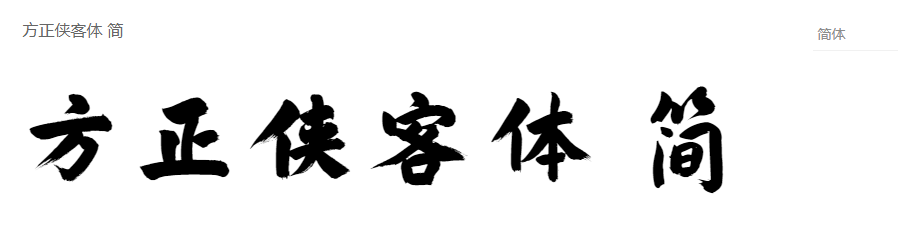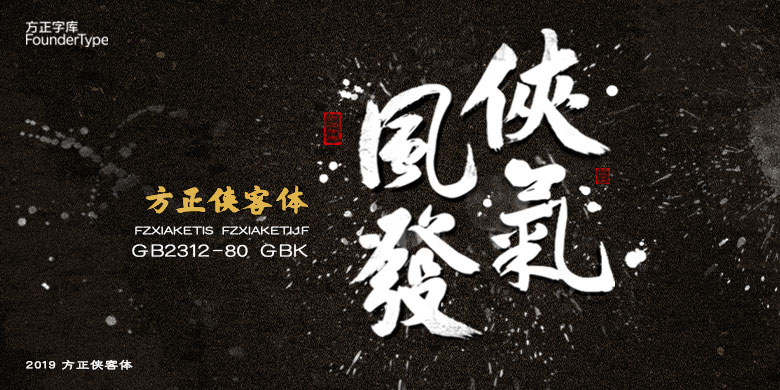
字体介绍:
方正侠客体的创作源自设计《评书聂隐娘》出版物,写字如挥剑,讲究轻重缓急,当时希望用这种斩钉截铁的率性书写来呈现侠客的潇洒与果敢。 古人云:“随心所欲不逾矩”,我们必须尊重传统、敬畏传统,在此基础上创作出具有时代特色的作品,侠客体的创作就是基于这样的理念。师法古代经典碑帖,比如颜真卿、张即之、朱熹等名家作品,字形以行楷为基准,尽可能保留笔画的丰富性,比如粗细变化、相同偏旁部首的变化以及飞白的效果等。作者希望创作一种既符合传统书法的笔法与结构,又能具有视觉设计张力的书法标题字体。主要适用于广告、包装、影视剧的标题等。
设计师: 张弥迪
分类:常规书写·毛笔